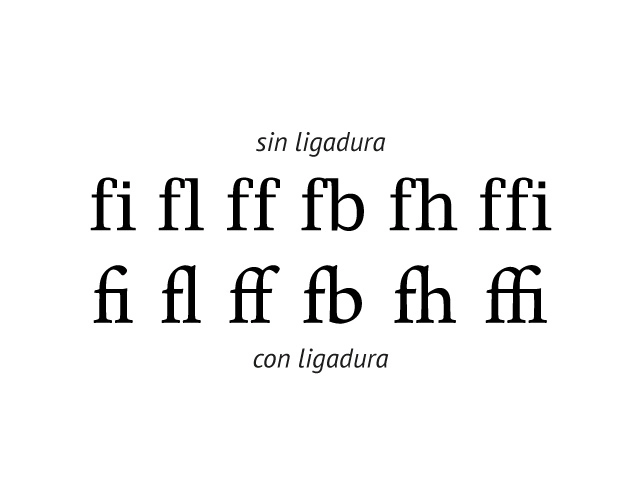
LIGADURA
Es un signo formado por la unión de dos o más signos, que a su vez pueden funcionar independientemente, cuya combinación se puede deber a herencias históricas de la escritura manual (ejemplo: la ligadura “et” llamada en inglés “ampersand”: &) o a correcciones estéticas de signos consecutivos (ejemplo: fi,fl)